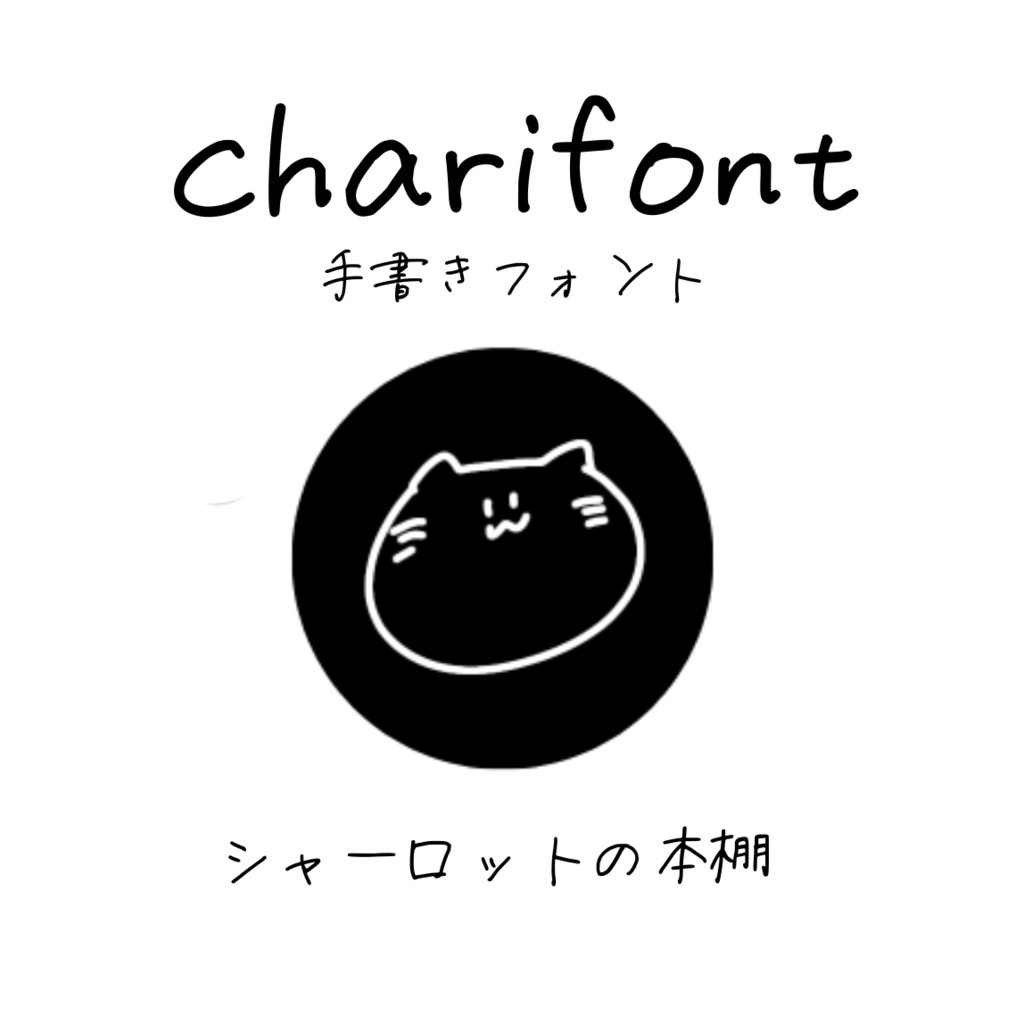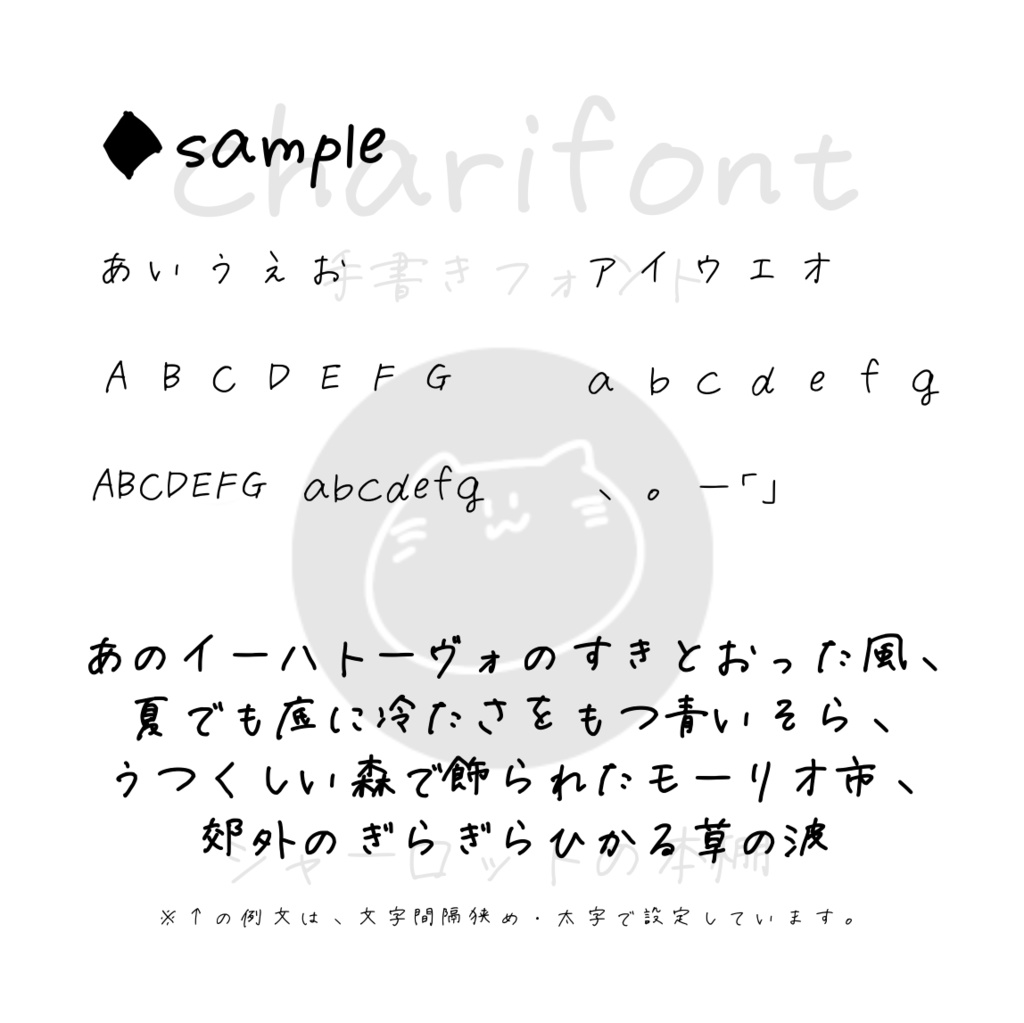
『charifont』 —手書きフォント
勢いでつくった作者(私)の手書きフォントです。 クレジット不要でフリーで使用いただけますが、動画や頒布物等で使用の際にご一報いただければ、喜びます…! 【利用規約】 ・商用・非商用を問わず利用可能です。(二次創作物への利用も◎) ・フリーフォントではありますが、著作権を放棄していません。自作発言をはじめ、フォントデータの改変・無断転載・再配布・販売は禁止とさせていただきます。 ・当フォントを利用して発生した、いかなる損害についても作者は責任を負いません。 【注意事項】 ・作者のお遊びで作成したフォントとなります。文字のがたつきや大きさのバランスが取れておりませんが、ご了承ください。 ・一部の端末、ソフトウェアでは使用できない場合がございます。 【その他】 ・登録文字:全角ひらがな・カタカナ、全角英数字、半角英数字、漢字(常用漢字)、句読点括弧等含む一部記号 ・文字間隔は狭めがおすすめです。 連絡はboothのショップメッセージまでお願いします。